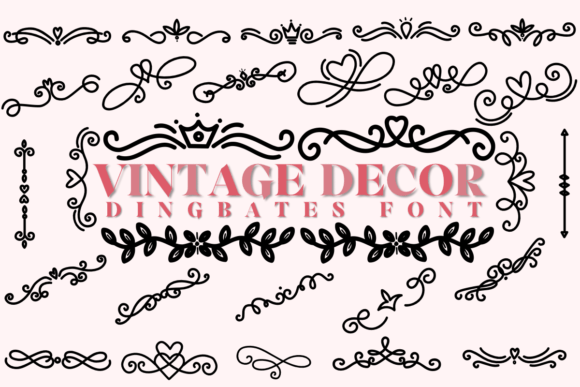
Vintage Decor
適切なデザイン要素を見つけるのは難しい場合がありますが、Vintage Decorは作品を即座に引き立てる優れたコレクションを提供します。
精密に作られたVintage Decorは、クリーンなベクター、滑らかなタイポグラフィ、そして安心のための商用ライセンスを提供します。
POD(オンデマンド印刷)製品、結婚式の招待状、またはソーシャルメディアのグラフィックを作成している場合でも、Vintage Decorは理想的です。